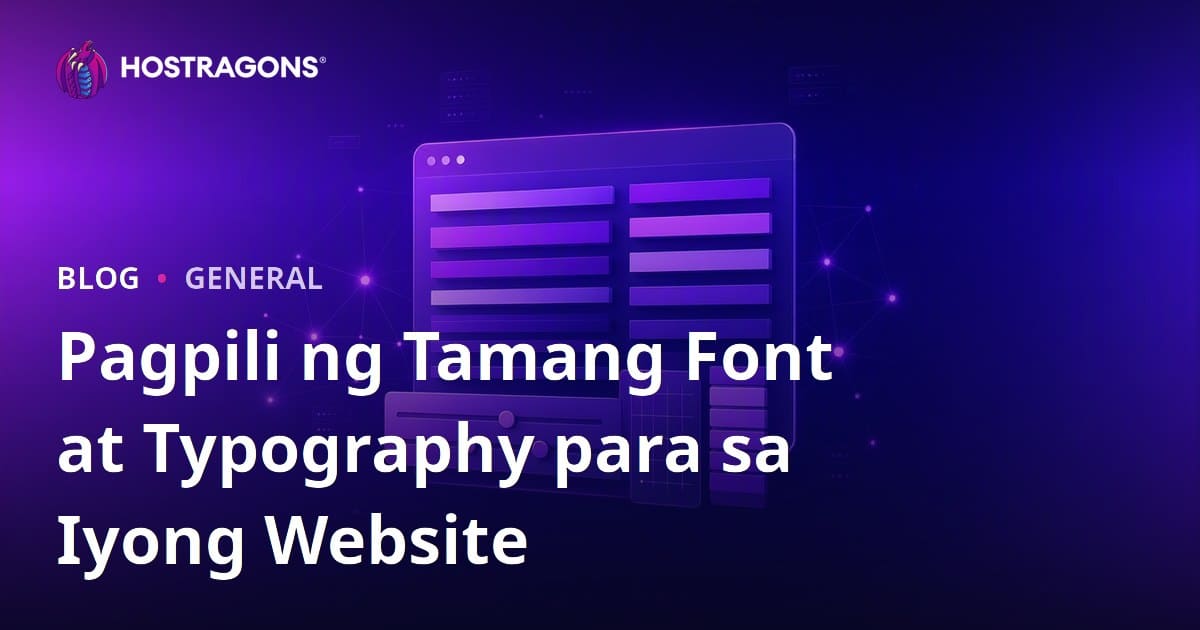
Ang pagpili ng perpektong font at typography para sa iyong website ay isang kritikal na elemento na direktang nakakaapekto sa karanasan ng gumagamit. Ang blog post na ito ay nagsasaliksik sa mga pangunahing prinsipyo na dapat mong bigyang-pansin kapag pumipili ng mga font para sa iyong website at kung paano mapahusay ng typography ang karanasan ng gumagamit. Habang ang impormasyon tungkol sa iba't ibang mga uri ng font at tampok ay ibinigay, ang mga inirerekumendang kumbinasyon ng font at mga gabay sa application ay tumutulong sa iyo na lumikha ng pinakaangkop na mga diskarte sa typography para sa iyong website. Gamit ang isang epektibong diskarte sa typography para sa iyong website, maaari mong maakit ang mga bisita at palakasin ang iyong imahe ng tatak. Sa ganitong paraan, ang iyong website ay magiging mas hindi malilimutan at madaling gamitin.
Mga Bagay na Dapat Isaalang-alang sa Pagpili ng Mga Font para sa Iyong Website
Ang pagpili ng isang font para sa iyong website ay higit pa sa isang aesthetic na pagpipilian, ito ay isang kritikal na elemento na direktang nakakaapekto sa karanasan ng gumagamit. Ang pagpili ng tamang font ay nagpapahusay sa kakayahang mabasa, nagpapalakas sa iyong pagkakakilanlan ng tatak, at pinapanatili ang mga bisita sa iyong site nang mas matagal. Samakatuwid, mahalaga na maging maingat at gumawa ng matalinong mga desisyon kapag pumipili ng mga font.
Kapag pumipili ng font, dapat mo munang isaalang-alang ang iyong target na madla . Ang edad, interes, at inaasahan ng iyong target na madla ay may mahalagang papel sa pagtukoy ng uri at estilo ng font na iyong pinili. Halimbawa, kung umaapela ka sa isang bata at dynamic na madla, maaari kang pumili ng mas moderno at naka-bold na mga font. Gayunpaman, kung mayroon kang isang website na naglalayong isang mas tradisyonal at propesyonal na madla, mas angkop na gumamit ng mas klasiko at nababasa na mga font.
- Mga salik na dapat isaalang-alang sa pagpili ng font
- Mababasa: Ang font ay madaling basahin sa anumang laki.
- Pagkakakilanlan ng Brand: Sinasalamin ng font ang personalidad ng iyong brand.
- Pagkakasundo: Pagtutugma ng font sa pangkalahatang disenyo ng iyong website.
- Pagkakaiba-iba: Ipinapakita nang tama sa iba't ibang mga aparato at browser.
Sa talahanayan sa ibaba, maaari kang makahanap ng ilang mga halimbawa ng mga lugar ng paggamit at mga tampok ng iba't ibang mga uri ng font. Ang talahanayan na ito ay makakatulong sa iyo na pumili ng pinakaangkop na font para sa iyong website .
| Uri ng Font | Mga tampok | Mga Lugar ng Paggamit |
|---|---|---|
| Sheriff | Tradisyonal, pormal, madaling basahin | Mga pamagat, mahabang bloke ng teksto, akademikong publikasyon |
| Sans-Serif | Moderno, minimalist, malinis | Mga website, mobile app, maikling teksto |
| Iskrip | Elegante, personal, kaakit-akit ng mata | Mga logo, imbitasyon, mga espesyal na kaganapan |
| Pagpapakita | Naka-bold, orihinal, pandekorasyon | Mga headline, banner, patalastas |
Kapag pumipili ng isang font, mahalagang bigyang-pansin ang mga kumbinasyon ng font . Sa pamamagitan ng paggamit ng komplementaryo at maayos na mga font, maaari mong gawing mas kaakit-akit at propesyonal ang disenyo ng iyong website. Sa pamamagitan ng paggamit ng ibang font para sa mga heading at ibang font para sa teksto, maaari kang lumikha ng isang visual hierarchy at maakit ang pansin ng mga gumagamit. Tandaan na ang pagpili ng tamang font ay maaaring gumawa ng isang malaking pagkakaiba para sa iyong website .
Mga Paraan upang Madagdagan ang Karanasan ng Gumagamit sa Typography
Ang isa sa mga pinakamahalagang paraan upang mapabuti ang karanasan ng gumagamit (UX) ng website ay sa pamamagitan ng paggamit ng epektibong typography. Ang pagpili ng tamang font ay maaaring dagdagan ang oras na ginugugol ng mga bisita sa iyong website at dagdagan ang mga rate ng conversion sa pamamagitan ng pagsasama ng kakayahang mabasa, hierarchy, at mga elemento ng aesthetic. Kasama sa typography hindi lamang ang pagpili ng font kundi pati na rin ang mga kadahilanan tulad ng pag-aayos ng teksto, line spacing, kerning, at pangkalahatang pagkakasundo ng disenyo.
Ano ang Typography?
Ang tipograpiya, sa pinakasimpleng kahulugan nito, ay ang sining ng biswal na pag-aayos ng teksto. Ang kaayusan na ito ay naglalayong mapahusay ang kakayahang mabasa, maihatid ang mensahe nang malinaw, at mag-ambag sa pangkalahatang aesthetic ng website . Ang mahusay na typography ay nagbibigay-daan sa mga gumagamit na madaling maunawaan ang nilalaman at nagpapabuti sa karanasan sa pagba-browse sa iyong website .
Ang talahanayan sa ibaba ay naglalarawan ng mga pangunahing bahagi ng typography at ang kanilang epekto sa karanasan ng gumagamit:
| Bahagi | Paliwanag | Epekto sa Karanasan ng User |
|---|---|---|
| Pagpili ng Font | Pagpapasiya ng nababasa at angkop na mga font. | Pinapabuti nito ang kakayahang mabasa at pinalalakas ang imahe ng tatak. |
| Sukat at Timbang | Pagsasaayos ng mga laki at kapal ng teksto. | Lumilikha ito ng hierarchy, nagha-highlight ng mahahalagang impormasyon. |
| Nangunguna | I-edit ang espasyo sa pagitan ng mga linya. | Pinapataas ang pagiging madaling mabasa at binabawasan ang pagkapagod sa mata. |
| Kerning (Pagsubaybay) | Ayusin ang spacing sa pagitan ng mga character. | Nakakaapekto ito sa kakayahang mabasa, nagpapabuti sa hitsura ng aesthetic. |
Mayroong ilang mga paraan upang ma-optimize ang mga font upang hindi ito makaapekto sa pagganap ng iyong website. Una, gamitin ang mga font na talagang kailangan mo sa iyong website at iwasan ang mga hindi kinakailangang font. Pangalawa, bawasan ang laki ng mga file ng font sa pamamagitan ng pag-compress ng mga ito. Pangatlo, gawing mas mabilis ang pag-load ng iyong website sa pamamagitan ng pag-preload ng mga font. Pang-apat, pagbutihin ang pagiging tugma at pagganap sa pamamagitan ng paggamit ng iba't ibang mga format ng font (WOFF, WOFF2) para sa iba't ibang mga aparato.